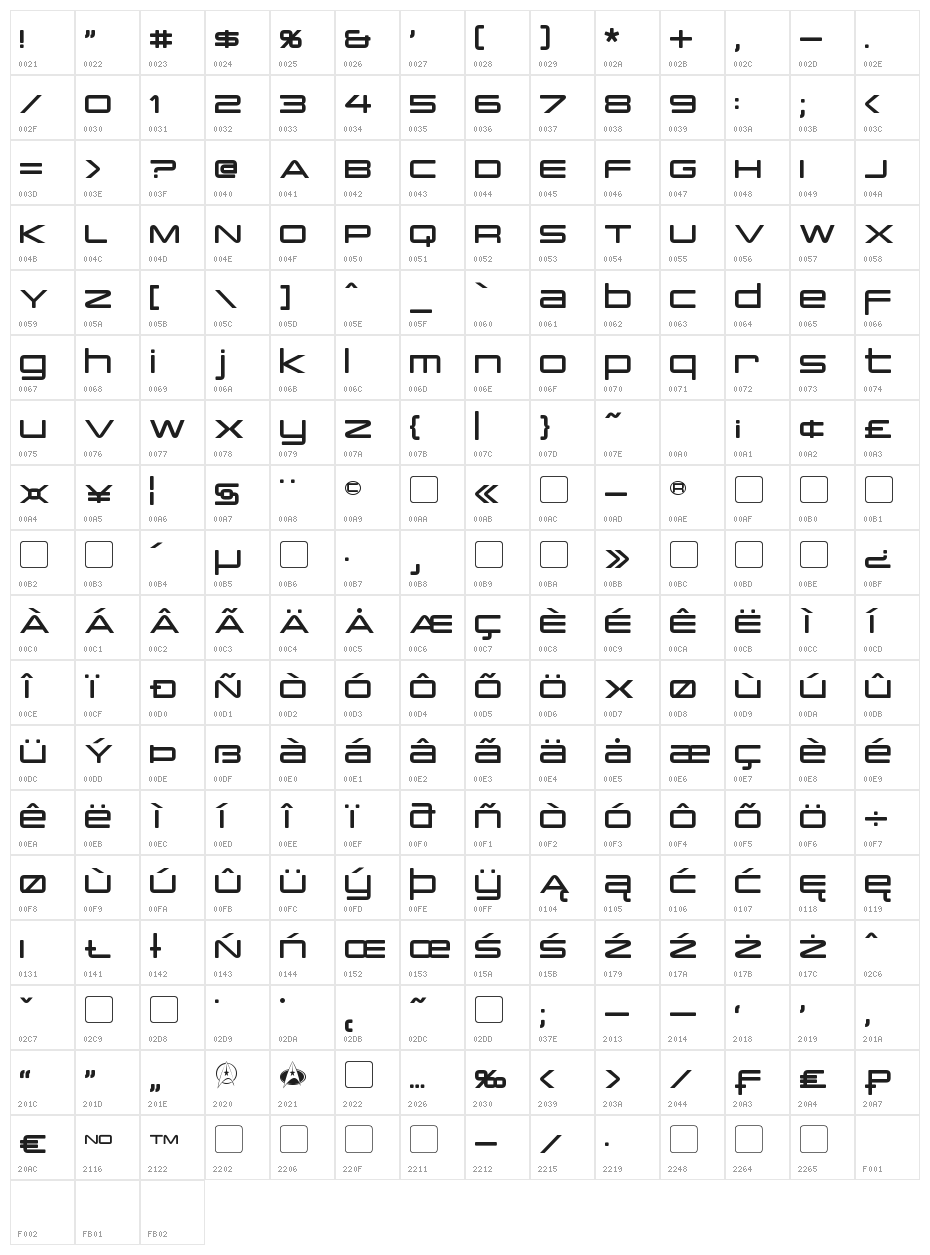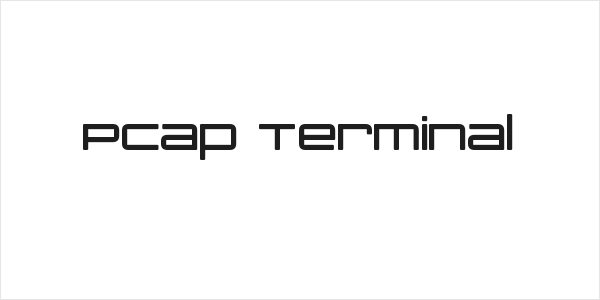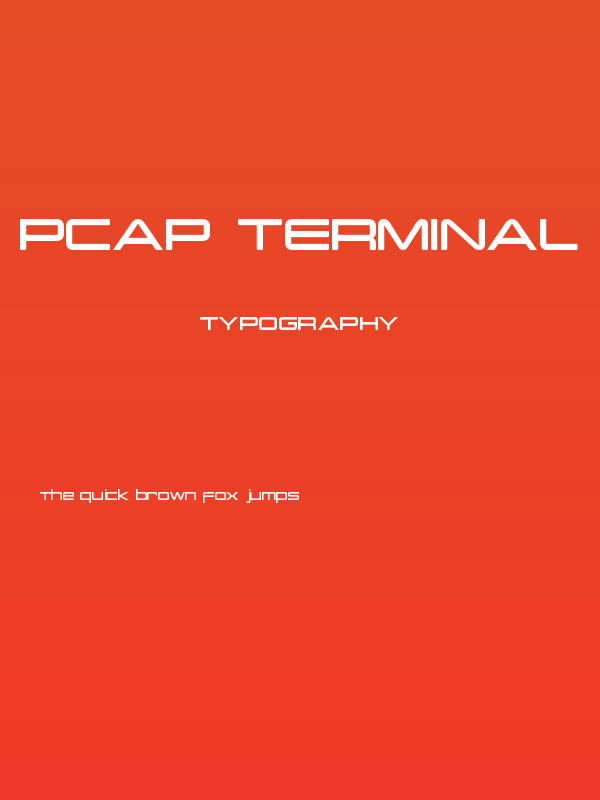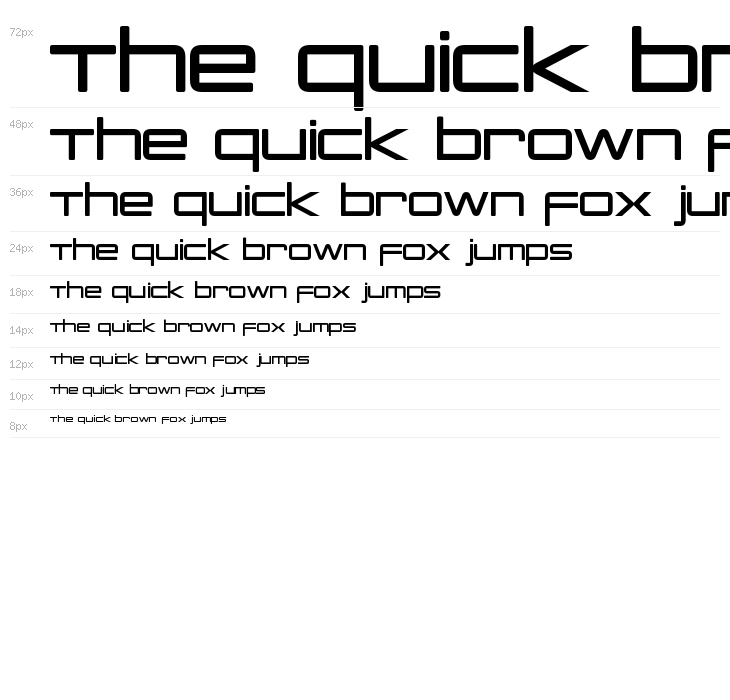
PCap Terminal Font
| Caz de utilizare | Headlines, Logos, Digital interfaces |
| Proiecte propuse | Ideal for tech branding, digital interfaces, video game design, and futuristic-themed projects. |